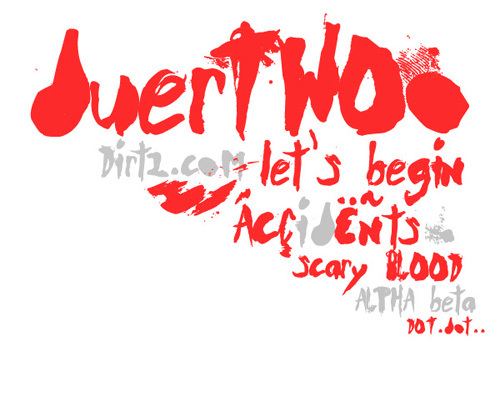
Vorschau der Schriftart DuerTWOo
Duer TWOo von Dirt2.com ist eine kostenlose, raue Pinsel-Display-Schrift mit gezackten, tintenlastigen Strichen. Seine Buchstaben neigen und verdrehen sich wie schnell handgemalte Schriftzüge. Einige Formen verjüngen sich zu scharfen, krallenartigen Spitzen.
Merchandise ist ein besonders geeignetes Medium, da die unruhige Schrift zu Band-Shirts und Skate-Grafiken passt. Sie kann Musikpostern und Game-Artworks zudem eine ungezähmte Note verleihen. Die spitz zulaufenden Silhouetten lassen einen Titel zu einem Teil eines Kreaturen-Emblems werden, anstatt ein gewöhnlicher Schriftzug zu bleiben.
Präsentation und Schriftprobe von DuerTWOo
Zeichentabelle der Schriftart DuerTWOo
Zeichentabelle von DuerTWOo: Basis-Lateinisch, Seite 1
Glyphen der Schriftart DuerTWOo — Basis-Lateinisch, Seite 1